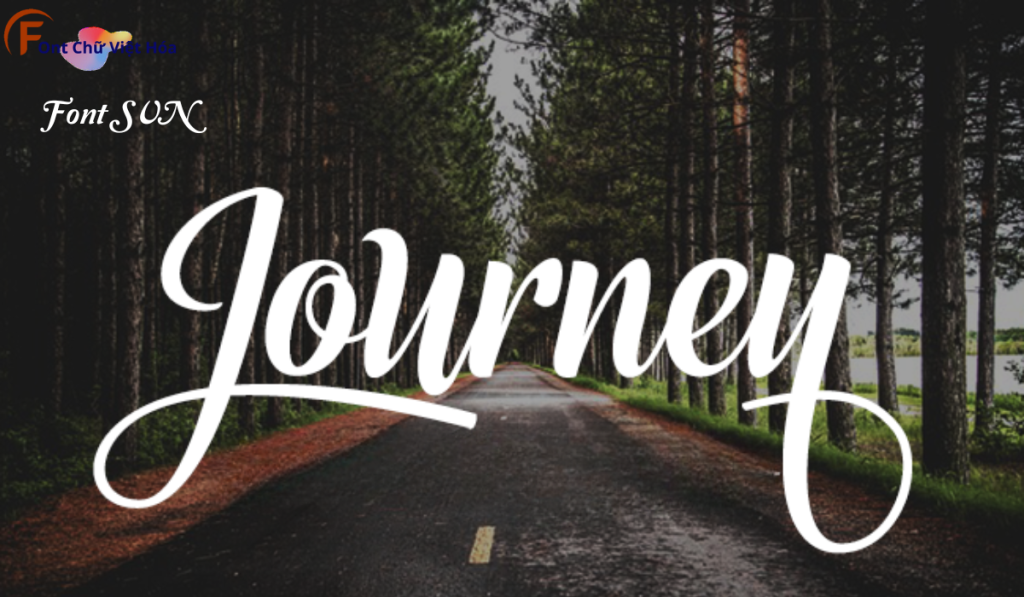
Font SVN Journey Việt Hóa
Tác giả: SVN Journey
Ngày phát hành: 7/2024
Bộ Font: SVN
Font SVN Journey Việt Hóa là một font chữ không chân hiện đại, thuộc bộ font SVN. Được thiết kế với mục tiêu mang lại sự tinh tế và thanh lịch, font này phù hợp cho các dự án thiết kế như website, tài liệu, và bao bì sản phẩm. Với các nét chữ rõ ràng và độ dày đều đặn, Font SVN Journey Việt Hóa không chỉ dễ đọc mà còn tạo cảm giác chuyên nghiệp. Việc Việt hóa font giúp người dùng dễ dàng sử dụng trong các thiết kế tiếng Việt, mang lại sự tiện lợi và thẩm mỹ cao.